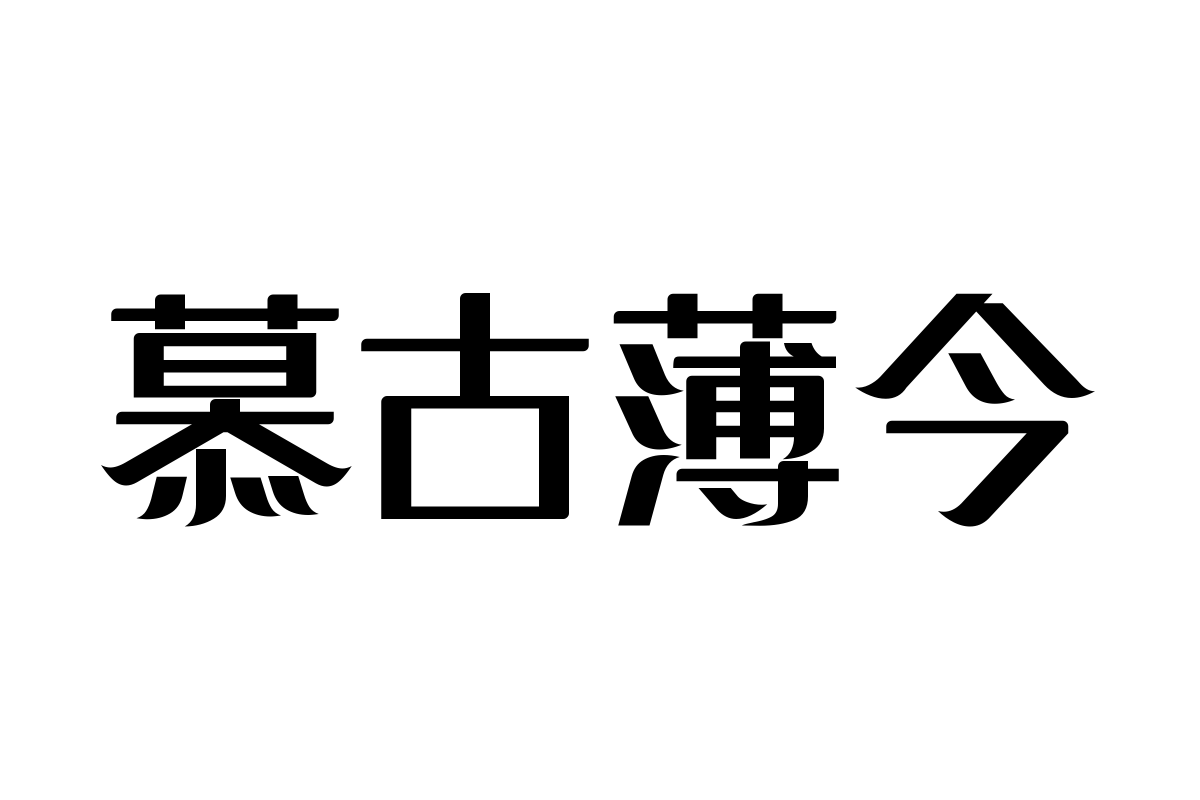
三极能量黑是款非常实用的字体,它以简洁、现代的设计风格为主,适合用于各种需要强调文字清晰度和易读性的场合。这款字体的特点是笔画粗细适中,结构紧凑,能够很好地传达出清晰、简洁的信息。同时,由于其笔画数量较少,所以也非常适合用于制作电子文档或网页设计。总的来说,三极能量黑是一款非常实用的字体,无论是在印刷还是电子显示方面都能表现出色。